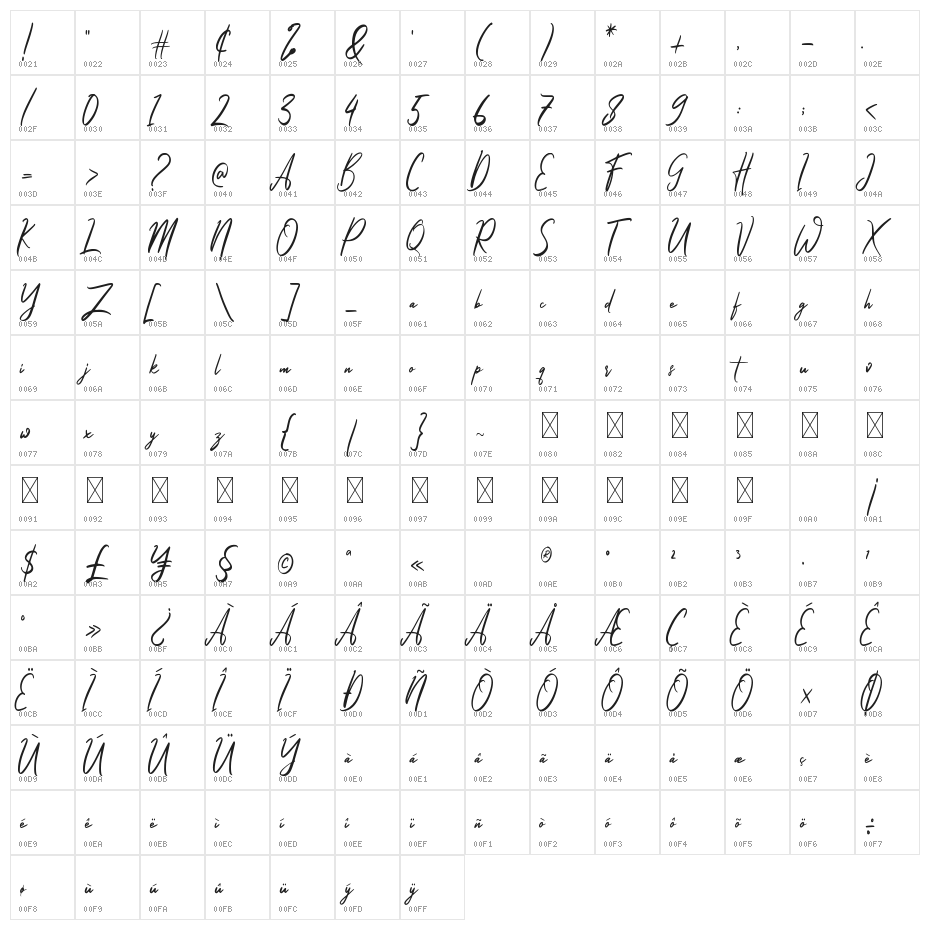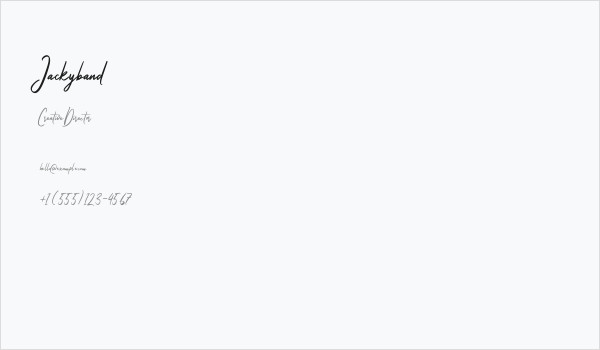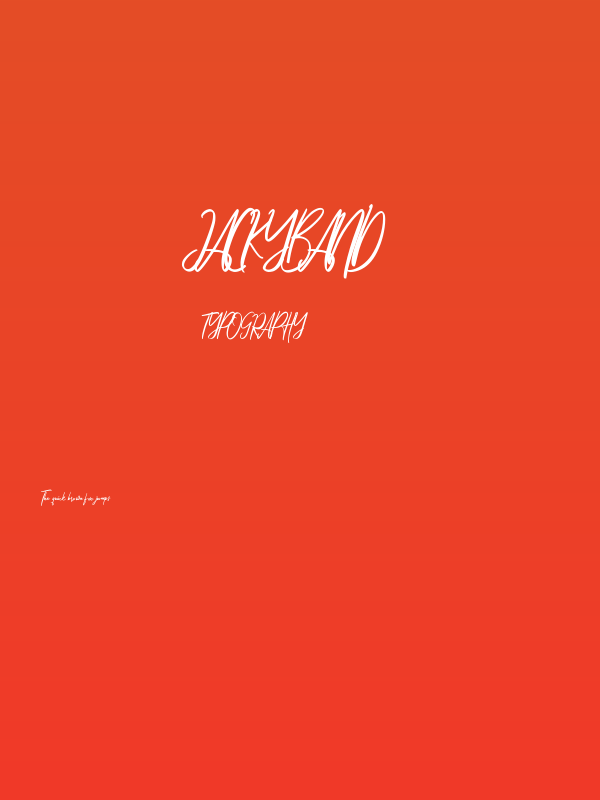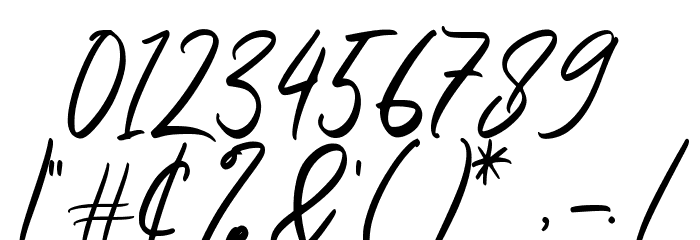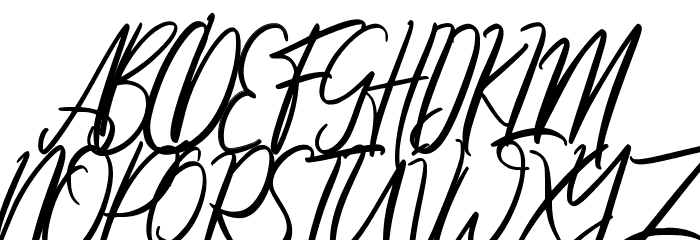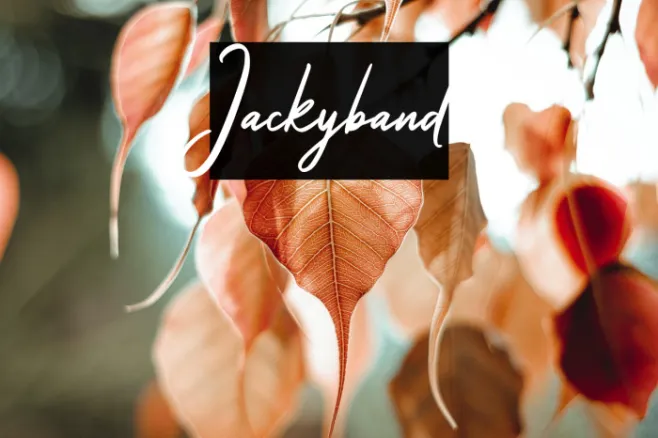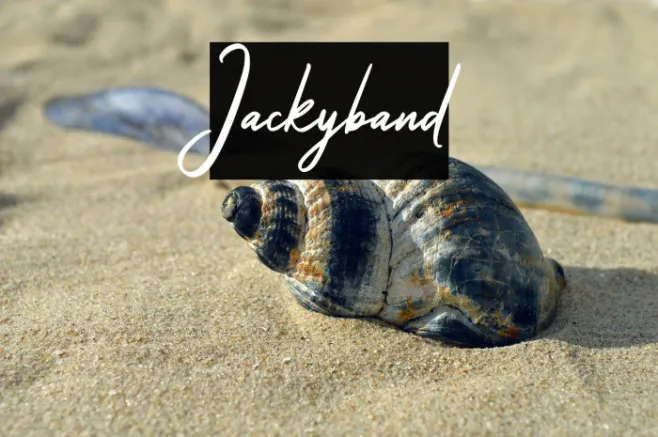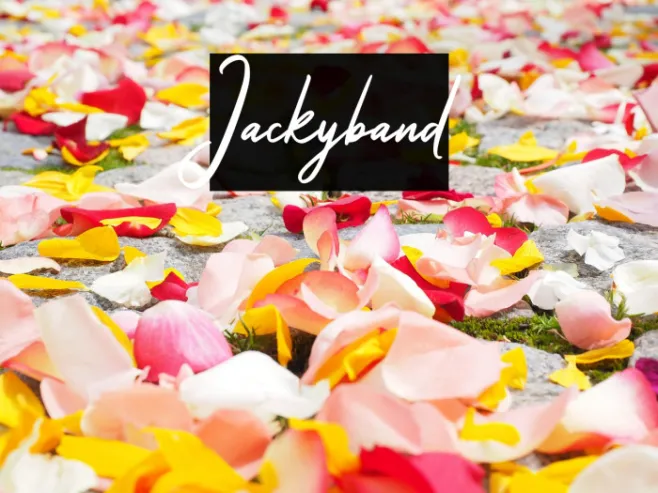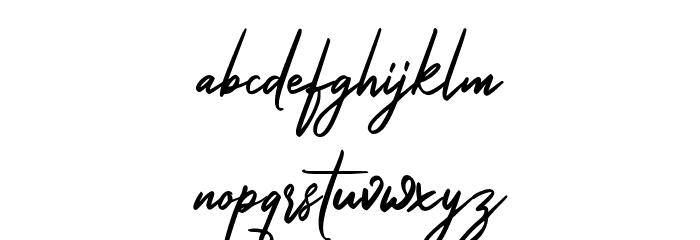
Jackyband Font
| Gesamtstil | Decorative, Expressive, Modern |
| Anwendungsfall | Logos, Headlines, Invitations, Artistic projects |
| Vorgeschlagene Projekte | Event invitations, personal branding, expressive headlines, artistic posters, signature logos. |